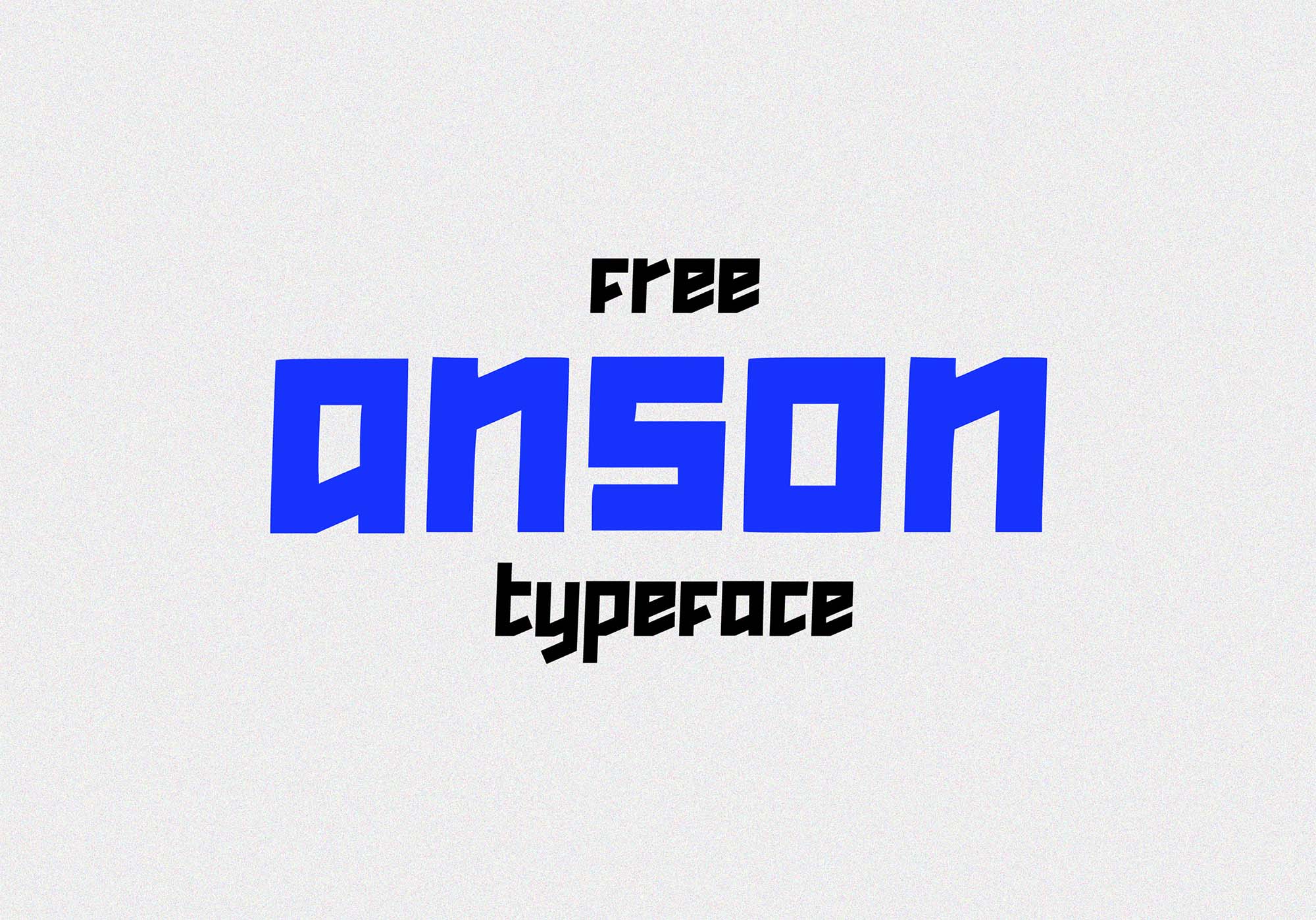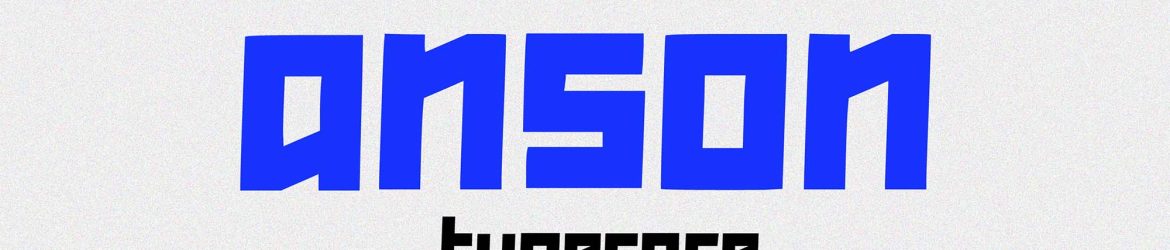
Anson Free Font é uma fonte de tipo moderna que combina elementos geométricos, representações estéticas e personagens fortes para criar uma impressão poderosa. Suas linhas retas e curvas arredondadas oferecem um visual moderno e atraente, adequado para uma ampla gama de aplicações gráficas. Esta fonte é perfeita para os projetos que deseja destacar, seja para assinaturas de propaganda, cartazes, design de camisetas, etiquetas, anúncios ou qualquer outro tipo de material gráfico. A Anson Free Font é uma opção elegante e versátil para qualquer designer que busca adicionar um toque único a seus projetos. Ela é a escolha certa para projetar em um nível superior, garantindo um impacto imediato e memorável em qualquer projeto.